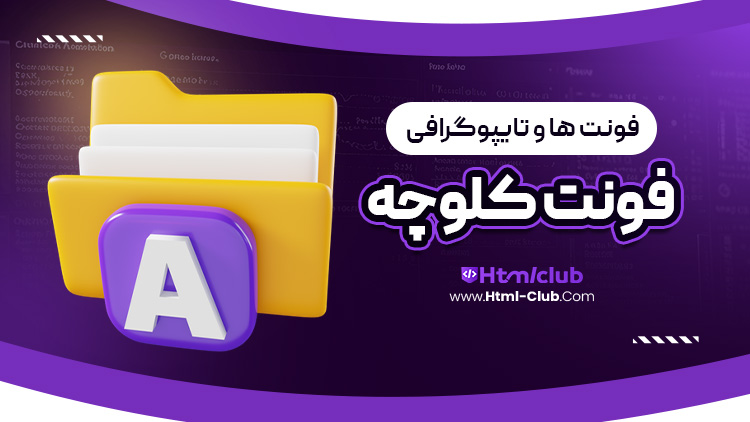
فونت کلوچه در سایت html club برای شما عزیزان قرار داده شده است.فونت کلوچه یک فونت فارسی با طراحی منحصر به فرد و جذاب است که به دلیل خطوط نرم و گرد خود، حس دوستانه و صمیمی به نوشتهها میبخشد. این فونت بهویژه برای طراحیهای غیررسمی، مانند کارتهای دعوت، بروشورها و پوسترهای هنری، بسیار مناسب است. فونت کلوچه بهخوبی میتواند در فضای دیجیتال و چاپی مورد استفاده قرار گیرد و به دلیل خوانایی بالا، تجربهای راحت برای مخاطب فراهم میکند. طراحی منحصر به فرد این فونت، باعث میشود که در میان فونتهای دیگر، به سادگی قابل تشخیص باشد و جذابیت خاصی به پروژههای گرافیکی اضافه کند.
ویژگی های برجسته فونت کلوچه :
فونت کلوچه با طراحی خاص و منحصر به فرد خود، به یکی از گزینههای محبوب در دنیای طراحی گرافیک تبدیل شده است. این فونت دارای ویژگیهای برجستهای است که آن را برای پروژههای مختلف ایدهآل میسازد.
طراحی دوستانه و صمیمی:
فونت کلوچه با خطوط نرم و گرد خود، حسی دوستانه و دلنشین را به متنها منتقل میکند. این ویژگی آن را به انتخابی مناسب برای طراحیهای غیررسمی و اجتماعی تبدیل میکند، از جمله کارتهای دعوت، بروشورها و وبسایتهای شخصی.
خوانایی بالا:
یکی از مزایای اصلی فونت کلوچه، خوانایی عالی آن است. این فونت بهویژه در اندازههای کوچک به راحتی قابل خواندن است و این ویژگی برای متون طولانی و مطالب آموزشی اهمیت زیادی دارد.
تنوع کاربرد:
فونت کلوچه بهخوبی با انواع پروژههای طراحی از جمله تبلیغات، بستهبندی محصولات و حتی محتوای دیجیتال سازگار است. این تطبیقپذیری به طراحان این امکان را میدهد که از آن در زمینههای مختلف استفاده کنند.
جذابیت بصری:
ظاهر منحصر به فرد فونت کلوچه به طرحهای شما جلوهای خاص و جذاب میبخشد. با این ویژگیها، فونت کلوچه به انتخابی خلاقانه و متمایز برای طراحان تبدیل شده است.
فونت کلوچه؛ شیرینی طراحی با خطوطی نرم و دلنشین! این فونت با زیبایی خاص خود، هر نوشتهای را به زندگی میآورد و حس صمیمیت را به کلمات شما میبخشد. با استفاده از کلوچه،
متنهای شما جلوهای دوستانه و جذاب پیدا میکنند و هر نگاه را به سمت خود میکشند. مناسب برای کارتهای دعوت، بروشورها و طراحیهای هنری، فونت کلوچه در هر پروژهای
میدرخشد. اگر به دنبال افزودن طعمی خوشمزه به طراحیهای خود هستید، با کلوچه هر کلمه را به یک جشن تبدیل کنید!